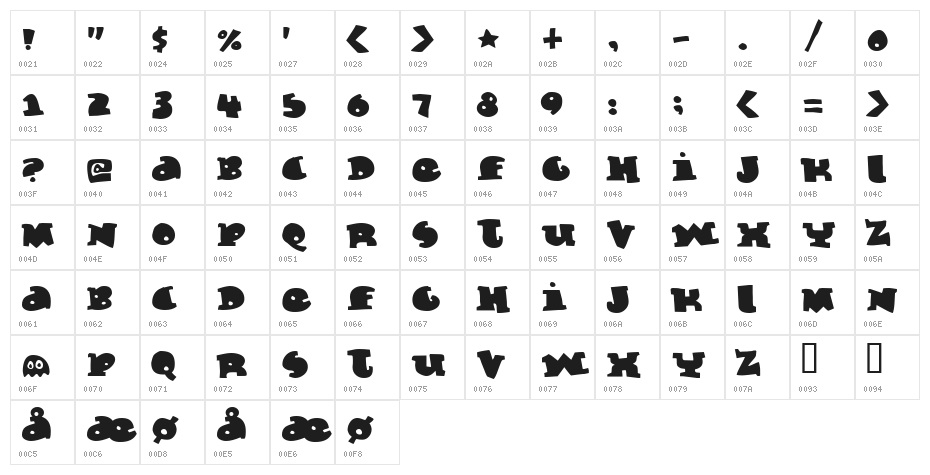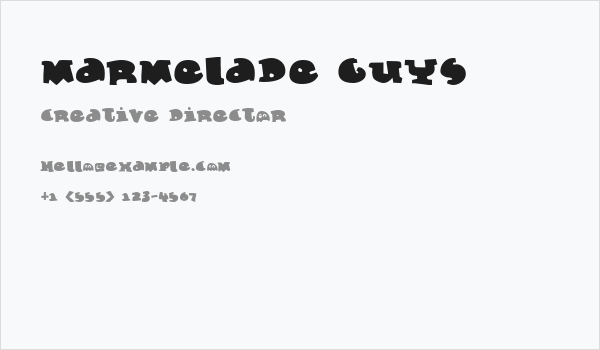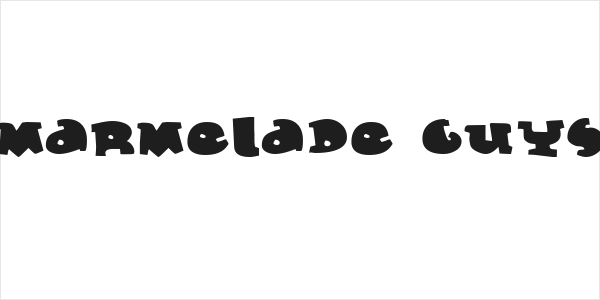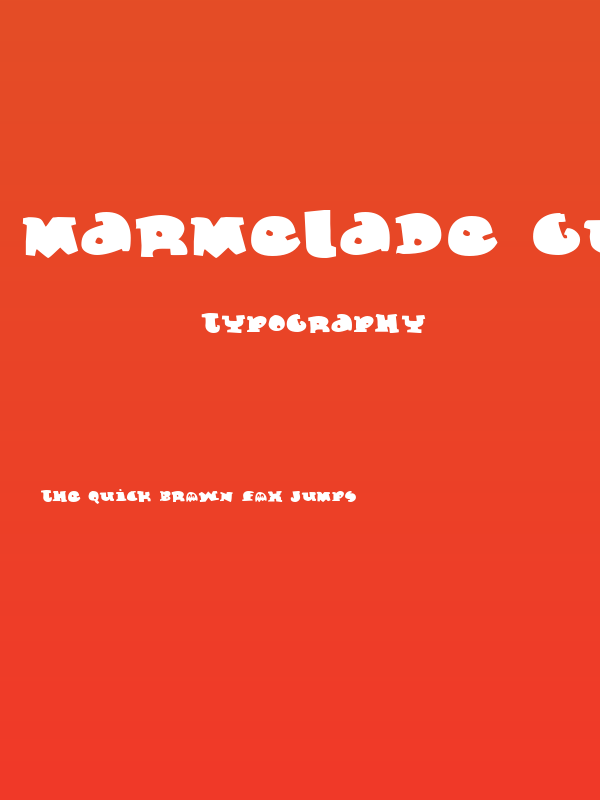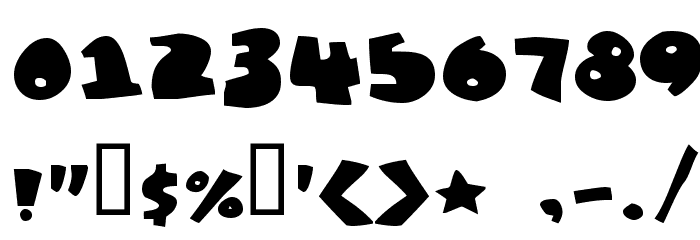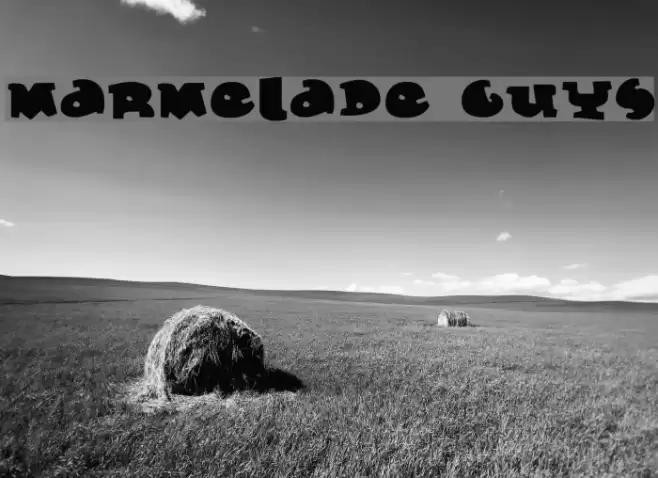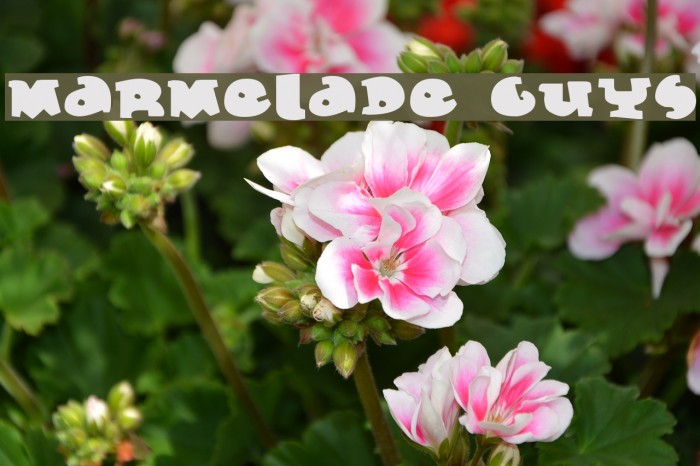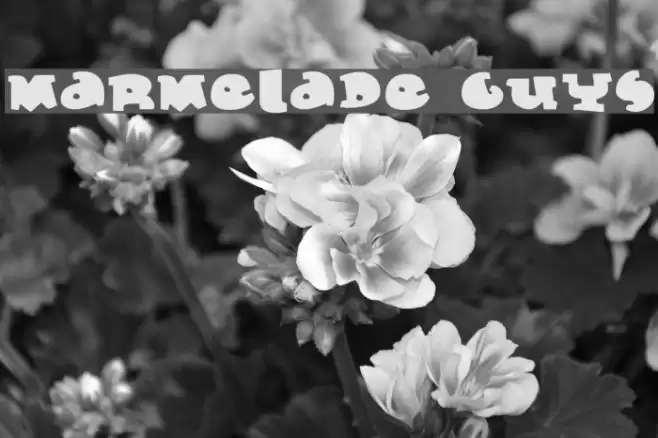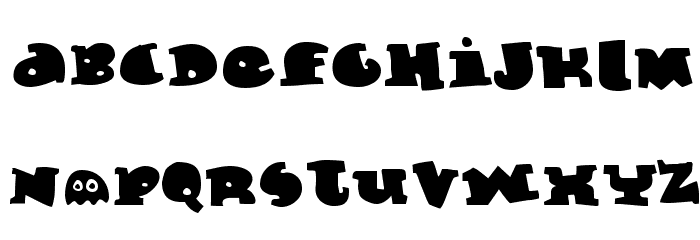
Marmelade Guys Font
| Gesamtstil | Playful, Cartoonish, Whimsical |
| Vorgeschlagene Projekte | Ideal for children's books, comic strips, playful branding, party invitations, and creative posters. |